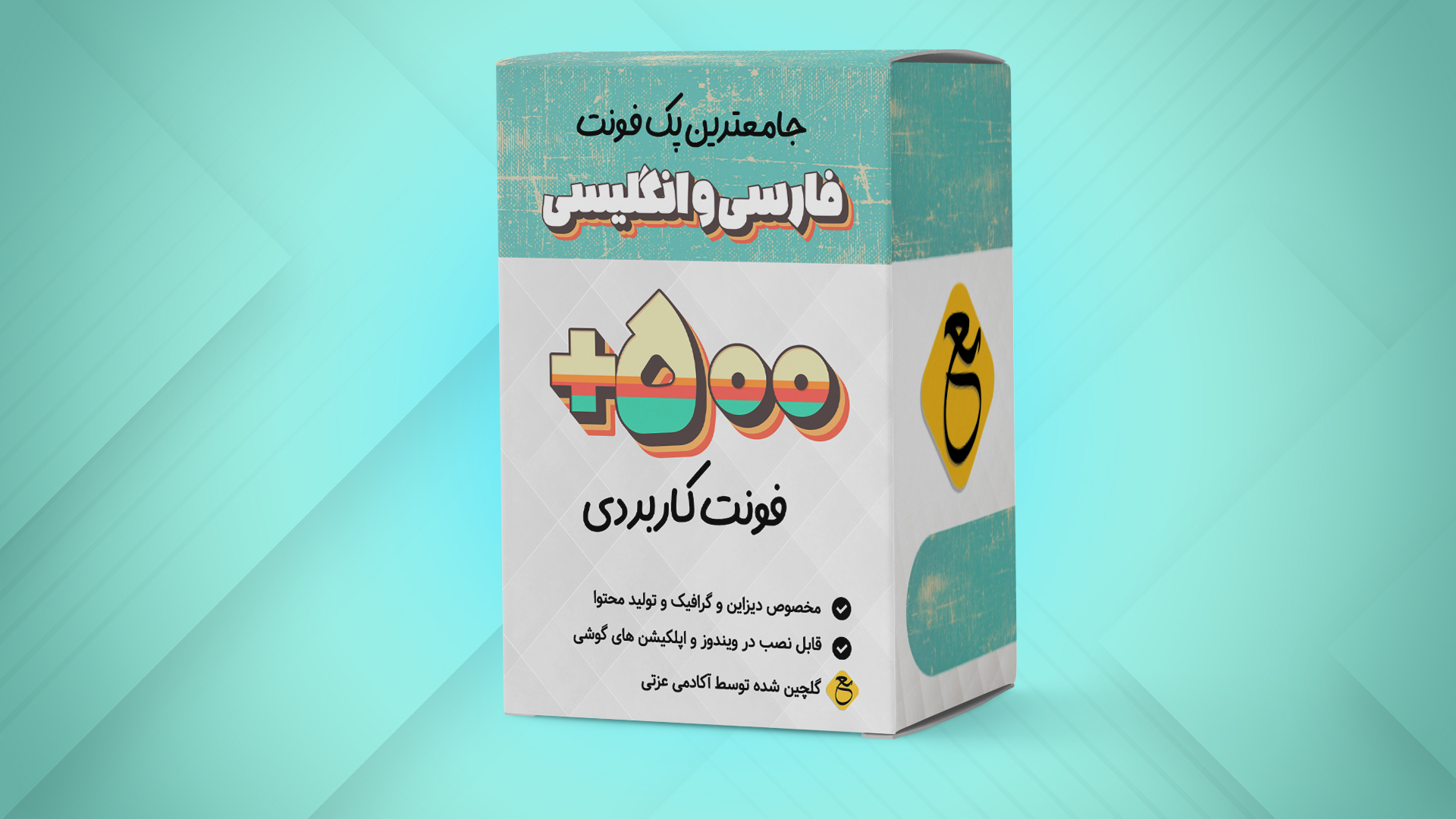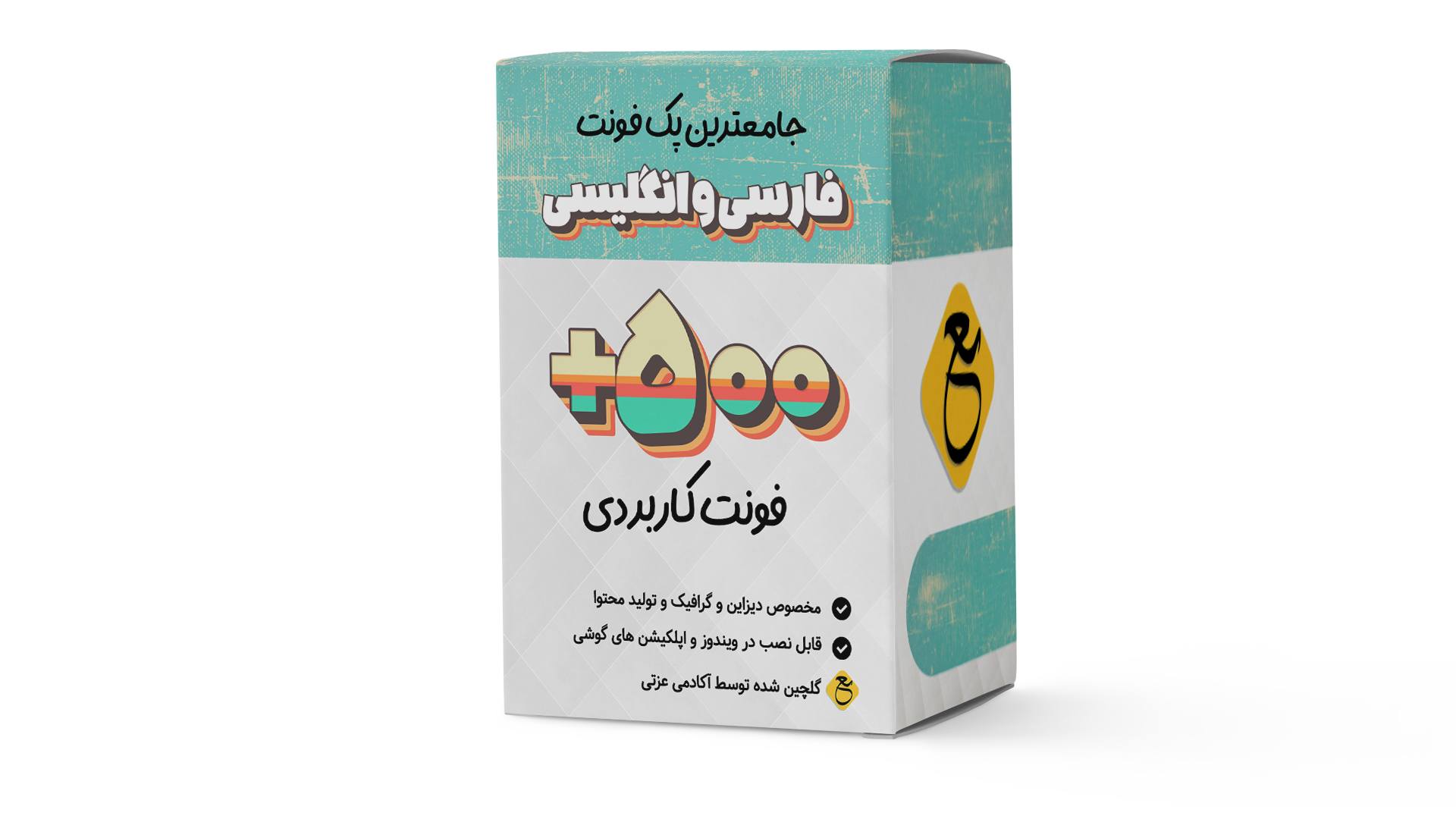
مجموعه فونت های زیبای فارسی
این پک مجموعهای گلچینشده از فونتهای فارسی و عربی است که طی سالها کار گرافیکی در آکادمی عزتی جمعآوری شده.
دقیقاً چه چیزی داخل پک است؟
۱٬۰۷۵ فونت در پوشهٔ font — شامل ۲۷۲ فونت گرافیکی و فانتزی فارسی، یک مجموعهٔ فونت فارسی و ۴۵ فونت لاتین تزئینی
۱٬۰۵۲ فونت عربی جدید (NEW Arabic Fonts)
۳۷۶ فونت مجموعهٔ Mj
۳۵۹ فونت مجموعهٔ Fonts 2021
۱۰۵ فونت مجموعهٔ font collection
۱۰۳ فونت ایرانی جدید
۷۸ فونت خانوادهٔ بهیج (Bahij)
۷۶ فونت مخصوص تایپوگرافی
۵۴ فونت لاینوتایپ فارسی و عربی
۵۴ فونت عربی
۳۵ فونت دستنویس
۳۰ فونت نستعلیق و خوشنویسی
۲۱ فونت اختصاصی (Exclusive)
۱۱ فونت در مجموعههای کوچکتر
این فونتها به چه دردی میخورند؟
تایپوگرافی فارسی و ساخت لوگو
عکسنوشته، کاور و استوری اینستاگرام
طراحی پوستر، بنر و کارت ویزیت
متنگذاری روی ویدیو در اپهای موبایل